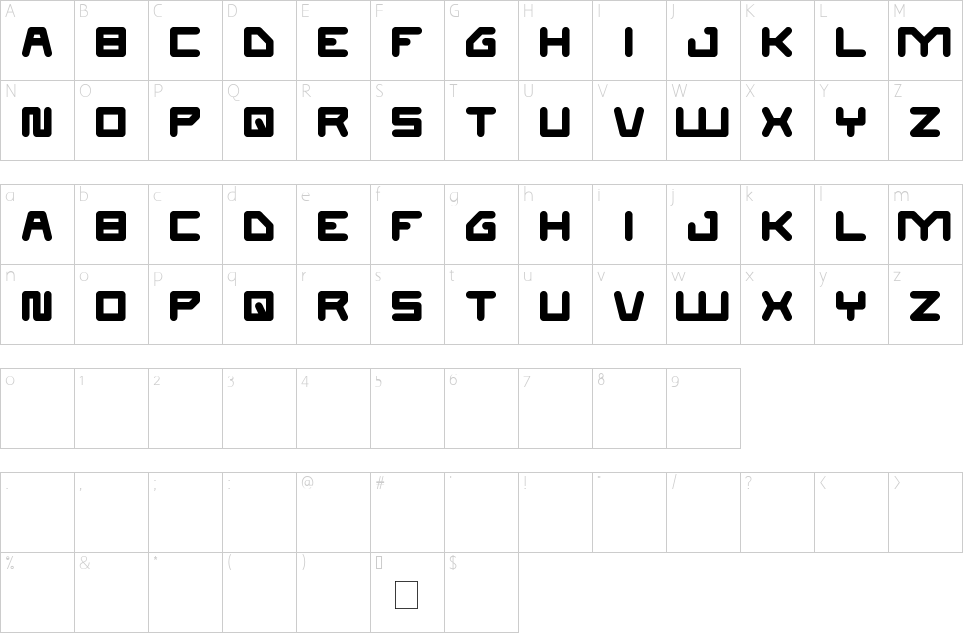
Athletic Font – Download Grátis
Através de uma fonte chamada Athletic, você pode adicionar um toque de energia e agilidade a suas criações digitais. Desenvolvida por weknow, esta fonte foi projetada para criar uma identidade visual forte e vibrante. Com um design leve e moderno, Athletic oferece uma ótima alternativa para quem está procurando uma fonte dinâmica para textos e logotipos. Disponível tanto para Windows quanto para Mac, esta fonte tem sido uma opção popular para quem procura um look minimalista e atemporal. Se você busca uma fonte que complementa a sua personalidade inovadora e ativa, Athletic pode ser a escolha perfeita. Já imaginou como ela se adaptaria ao seu próximo projeto? Download a font agora e descubra por si mesmo!